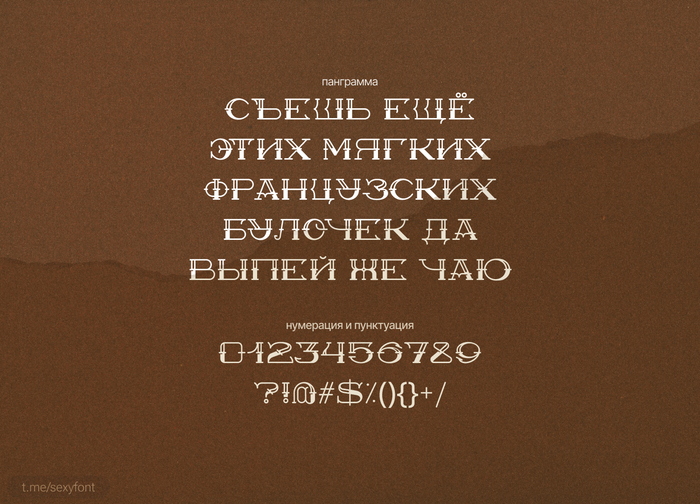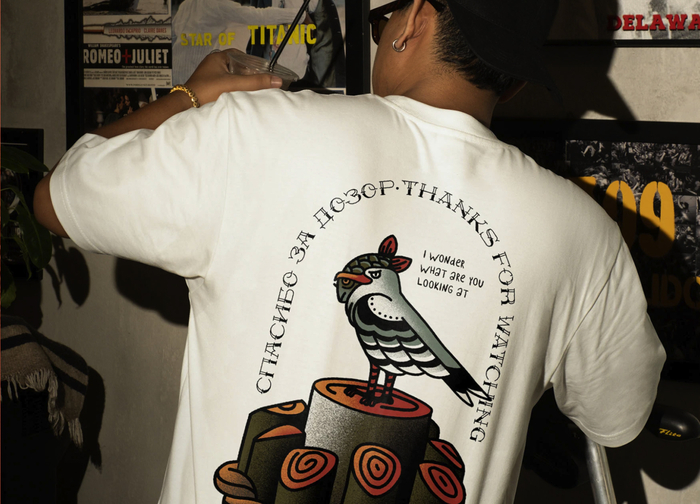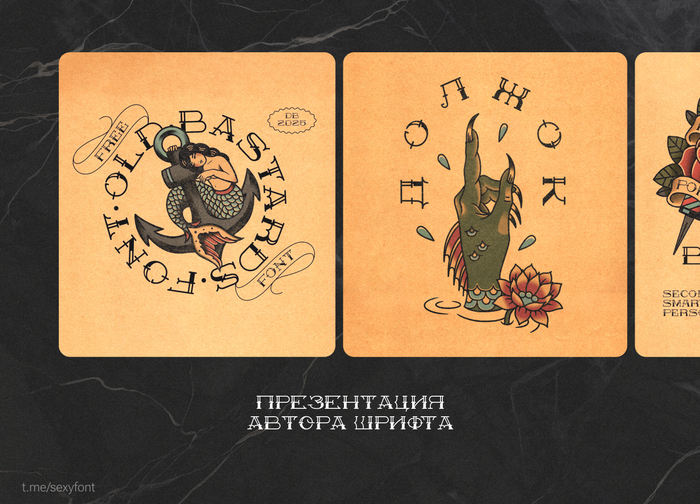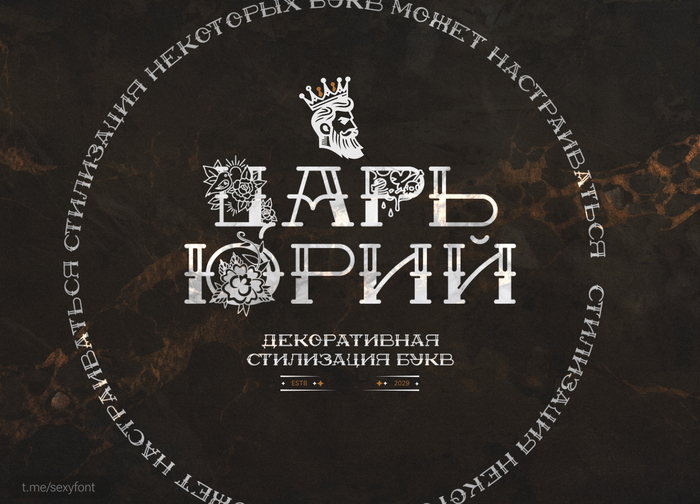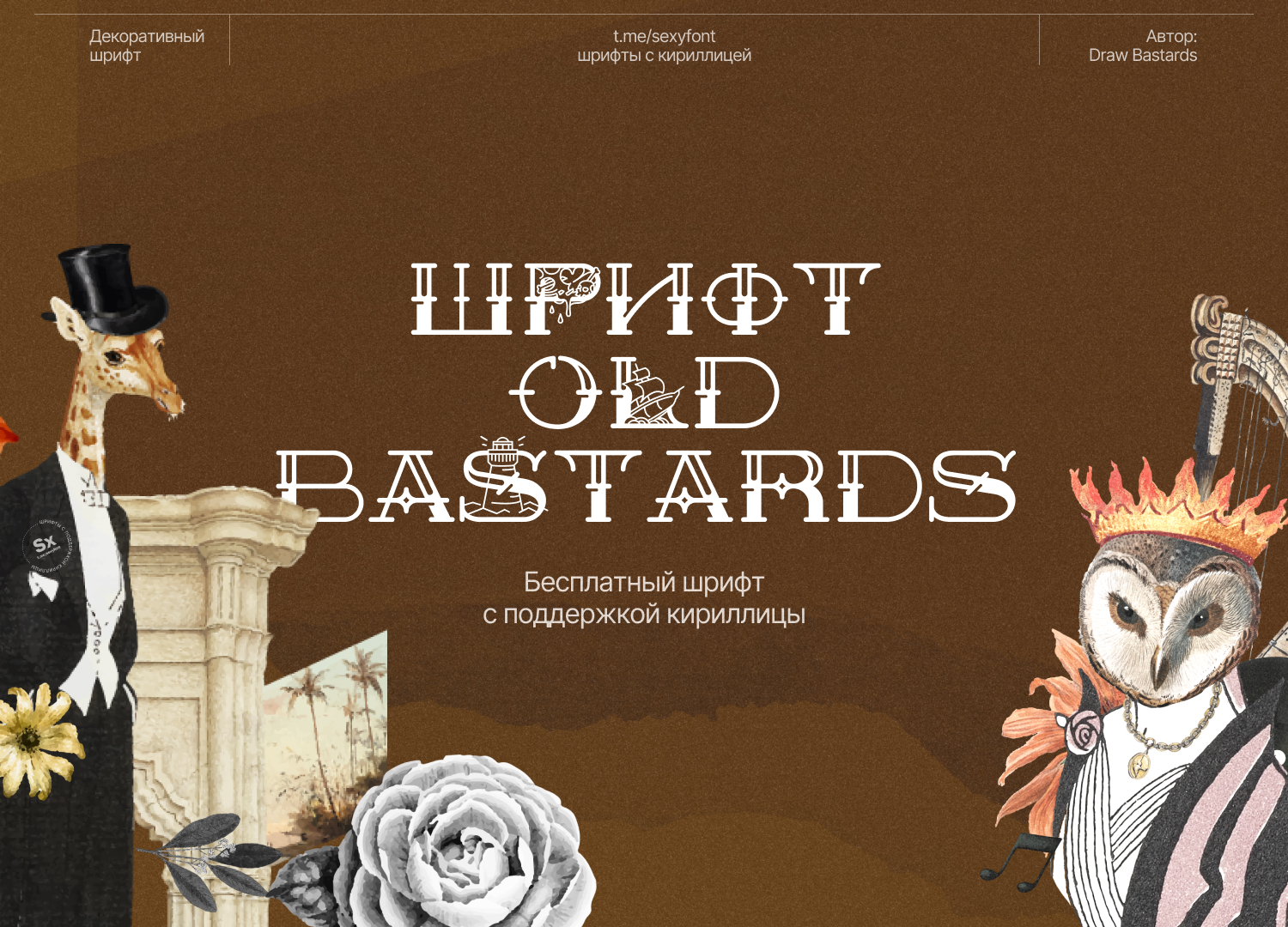
Шрифт Oldbastards. кириллица
Oldbastards — это бесплатный шрифт, вдохновлённый традиционными татуировками и духом американской олдскульной культуры. Идеально подойдёт для стильных, цепляющих заголовков, хулиганских цитат и рекламных слоганов.
Еще поддерживает пару вариантов букв) Мне понравились декоративные буквы.